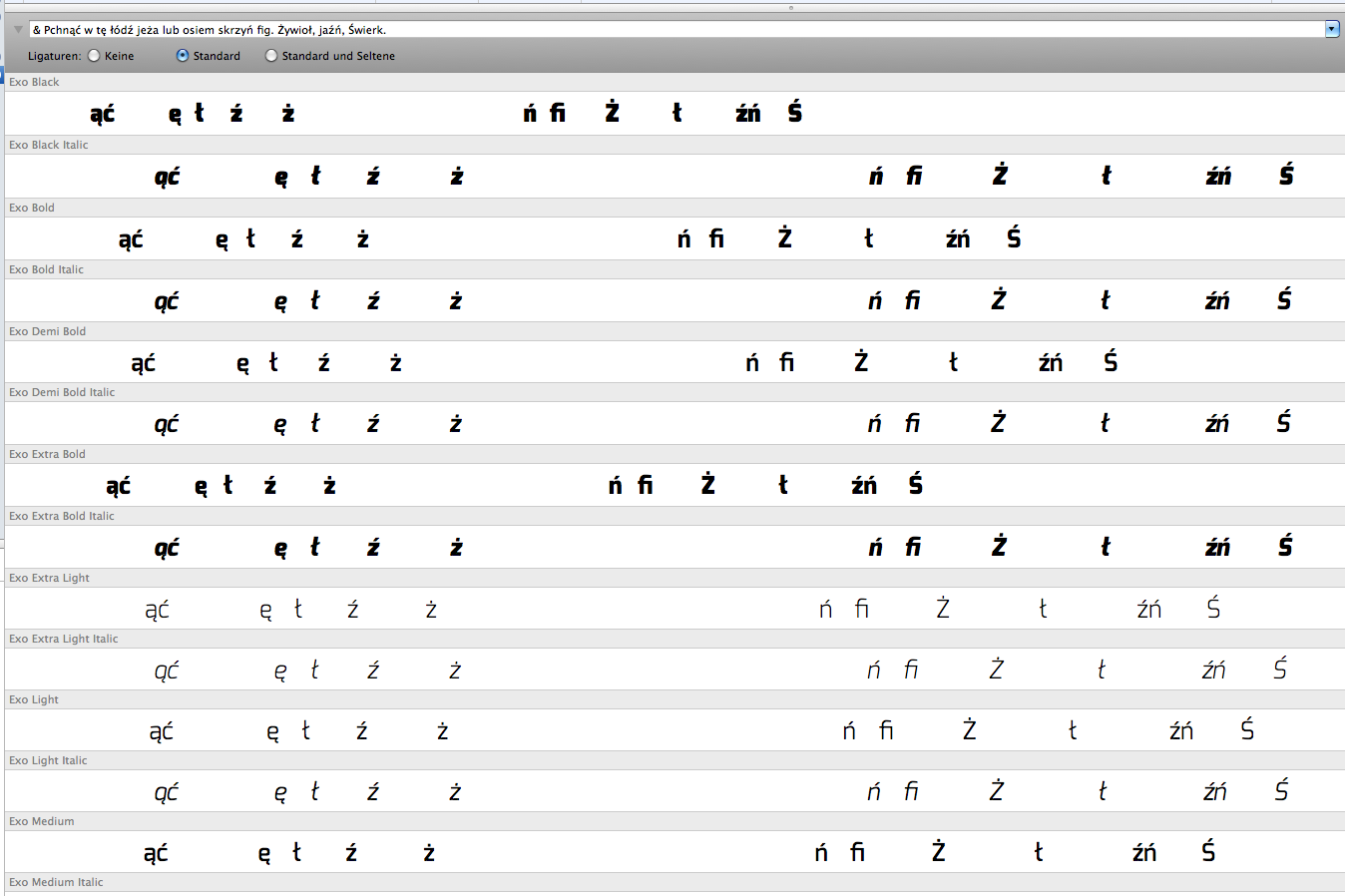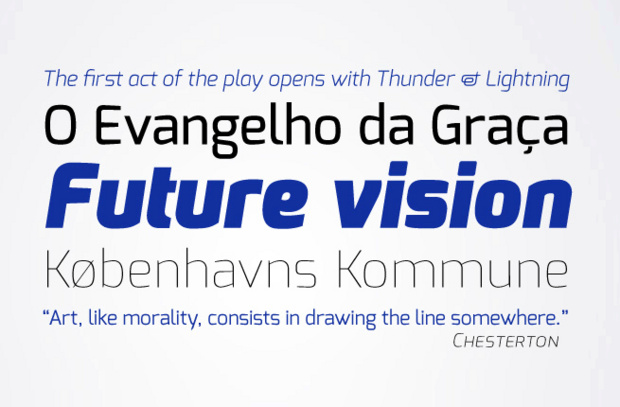
Crimson Text wird von hauptsächlich 3 Personen als Projekt für die Open-Source Gemeinschaft entwickelt. Eine Zielsetzung ist eine Textschrift zu entwickeln, welche angenehm aussieht und von einer möglichst breiten Masse als „General Purpose“ Schrift akzeptiert wird, und als solche als Ersatz für Times New Roman akzeptiert wird von einem uninformierten Leser eines Dokuments. Daher ist die Schrift zurückhaltend gestaltet. Des weiters fußt sie auf der Tradition der Strichführung von Renaissance-Antiqua Schriften. Auf diese Tradition gibt es kein Urheberrecht. Jeder kann eine Renaissance-Antiqua gestalten.
Wenn Crimson Text der Minion ähnlich ist, dann nur weil Slimbach für Minion die absolut identische Zielsetzung hatte: Eine auf der Renaissance basierenden Textschrift, zurückhaltend und zugänglich für die breite Masse, die als Ersatz für TNR dienen kann. Zwei ähnliche Zielsetzungen, zwei ähnliche Produkte. Die Vielfalt der Wahl ist doch etwas gutes.
Hinter dem Projekt stecken seit 2010 viele Arbeitsstunden dreier Personen und die Schrift wurde vom Start weg in unabhängiger und originärer Arbeitet gestaltet.
In der Gestaltung des kleinen /f/ finde ich Crimson Text der Minion sogar überlegen, da das Minion-/f/ mit den Umlauten der deutschen Sprache nicht kompatibel ist!
Dies ist auch der Grund warum ich persönlich von Crimson Text begeistert bin. Denn obwohl nichts mit Grafik, Gestaltung oder ähnlichem zu tun habe, besitze ich ein paar Schriften, darunter auch Minion, Adobe Caslon und Stone Type Foundrys Cycles, finde ich gibt es kaum gute Renaissance oder Barock Antiquen, welche man im Deutschen unbedarft einsetzen kann. Zu dieser Liste gehören zwar einige, jedoch gibt es oft einen Punkt der für mich einer „General Purpose“ Schrift im Wege steht. Die sind entweder relativ teuer (Andron, Albertina, Kis Antiqua Now), oder nicht zurückhaltend genug/zu lebendig (Arno, Stempel Garamond), oder die „x-height“ ist doch eher traditionell und klein (Williams Caslon), oder ist auf die eine oder andere Art nicht umfangreich genug (Cycles mit Regular, Italics und Semibold Schnitten, Rawlinson ohne italics Kapitälchen). Weiters gibt es die Lyon Text, Calluna, oder Erato, welche mir zu „digital/reduziert“ in der Strichführung und Gestaltung sind, hier ist die Crimson etwas lebendiger, oder die neue Equity, welche sogar noch enger ist als Times New Roman und mir dadurch das Schriftbild nicht so gut gefällt. Die Crimson füllt hier eine Lücke, die in einer gewissen Preisklasse sonst nur Minion füllt, und ist darüber hinaus besser im Deutschen zu gebrauchen.
Natürlich kann man das /f/ der Minion anpassen lassen in der Font-Datei, nur das kostet extra und ich finde es ist eigentlich fast ein Defekt einer Schrift, wenn diese für eine Sprache angeboten wird, dann jedoch die einzelnen Zeichen kollidieren.
Ich stehe nicht einmal mit dem Entwickler-Team von Crimson in irgendeiner Verbindung. Ich bin einfach froh, dass es die Schrift gibt, da sie für mich eine Lücke schließt. Mit evt. kleineren Fehlern einer freien Schrift kann ich leben, da ich nicht professionell damit arbeite, die f+Umlaut Kollision ist allerdings mein „Pet Peeve“, ein triviales Ärgernis, ein Dorn im Auge. :nicken:
Du siehst ja bestimmt die Liste der Schriften welche ich recherchiert und verglichen habe. :roll: Falls es wirklich an der Qualität scheitern sollte, habe ich ja noch andere Optionen (Cycles Eleven, Minion, Adobe Caslon). Und bis ich mir den Luxus einer Andron oder Kis Antiqua Now leiste, habe ich hiermit eine tolle Alternative.
Könntest du mal bitte genauer erläutern, was du da so an der f+Umlaut-Sache schlecht findest? Ich mit meinem Laienblick entdeckt nichts schlimmes.
Es sieht halt bescheiden aus, wenn der f-Bogen einen Umlautpunkt überlappt. Außerdem ist nicht zu vergessen, daß in all diesen Schriften das f auch folgende Oberlängenbuchstaben wie l oder b überlappt. Die Gestalter bedenken nicht, daß im Deutschen in Wörtern wie Aufbau oder Auflage kein Verbund steht. Und das ärgert mich ebenfalls sehr.
Es gibt ja genug Schriften, welche darauf achten, siehe meine Liste oben.
Allerdings sind gerade jene, die mir persönlich am meisten gefallen :oops: , auch die teuersten.
Professionelle Grafiker würden wohl einfach die Font-Datei selbst anpassen.
… Professionelle Grafiker würden wohl einfach die Font-Datei selbst anpassen.
Eher nicht. Zum einen dürften sie das gar nicht, zum anderen ist nicht jeder Grafiker auch ein Typograph.
… Zumindestens Adobe erlaubt Modifikationen.
Das hängt immer vom einzelnen Font ab und lässt sich so pauschal leider nicht sagen.
Eher nicht. Zum einen dürften sie das gar nicht, zum anderen ist nicht jeder Grafiker auch ein Typograph.
... oder Typedesigner 8-)
Auch das. Ich habe mit Typograph die Menschen gemeint, die sich handwerklich, gestalterisch, technisch usw. mit Typographie befassen.
Wow! 18 Schnitte mit tollen Opentype Features und das kostenlos. Aber beim genaueren Betrachten glaub’ ich, sie kommt für mich eher nur als Headline- oder Logofont in Frage. Im Fließtext macht sie mir bedauerlicherweise einen sehr holprigen Eindruck. Trotzdem, schöner Ansatz!